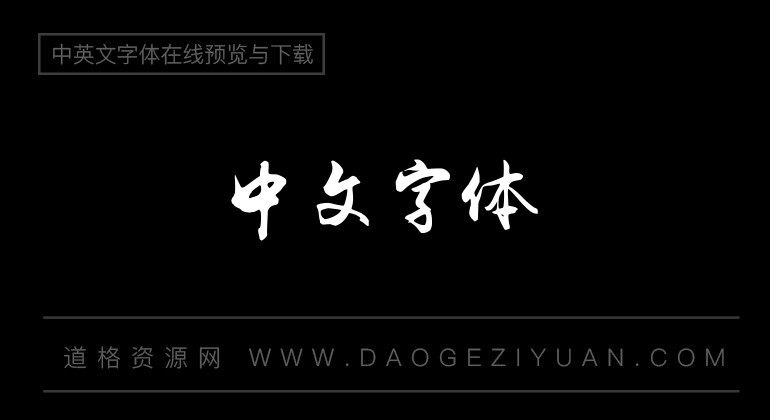
李旭科书法
李旭科书法是由李旭科先生创作的一种书法风格,他多年来不断探索,研究,发展,最终形成了自己独到的书法风格,他的字体特点是笔画挺拔有力,结构紧凑,笔画比例均衡,线条柔和,细节精细,笔墨浑厚,表现力强大,极具艺术感染力,能够表现出书法的精神和艺术美感。
李旭科书法是一款非常不错的手写艺术字体,具有很好的视觉感,适合于文化类的宣传设计、商业类品牌的广告和产品包装设计以及个性化文字排版等较多场景。